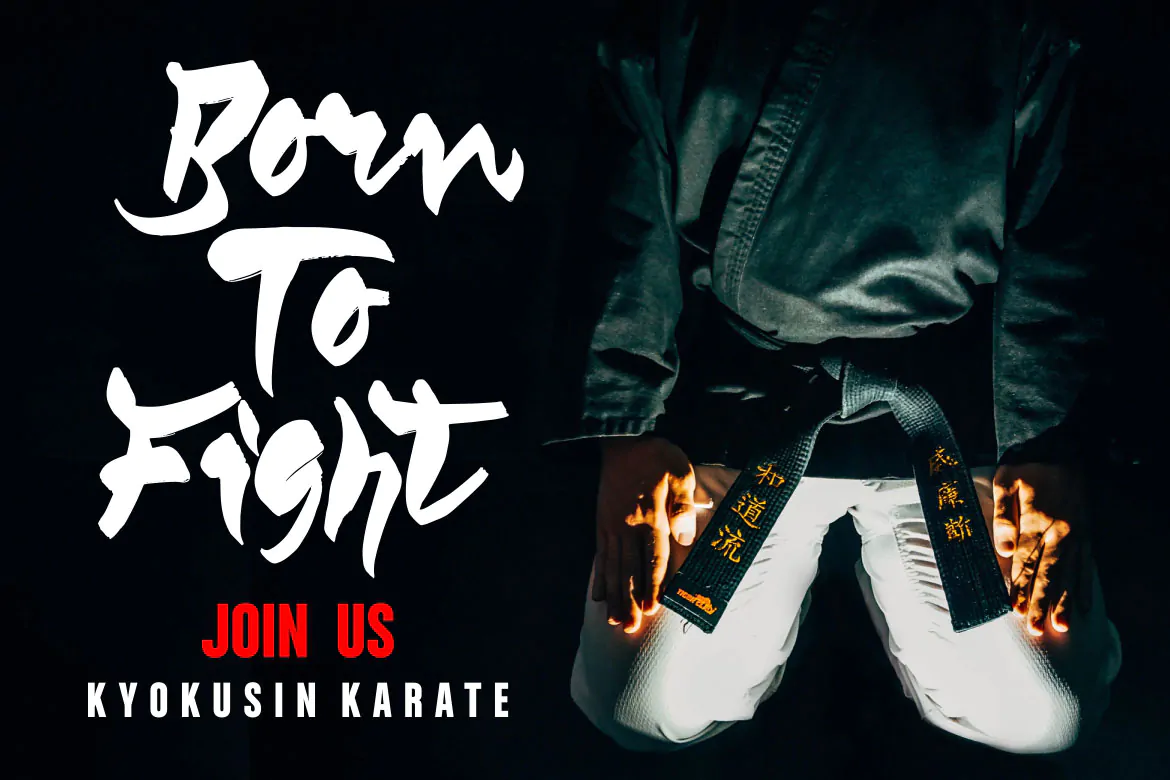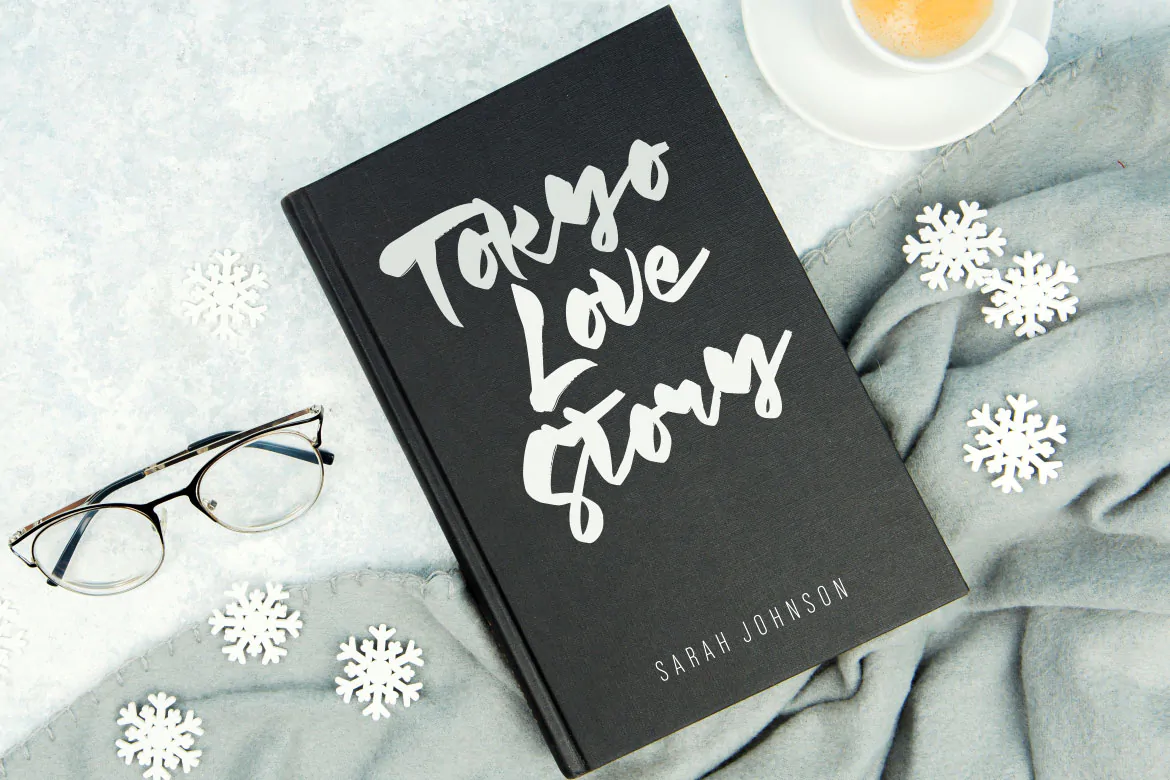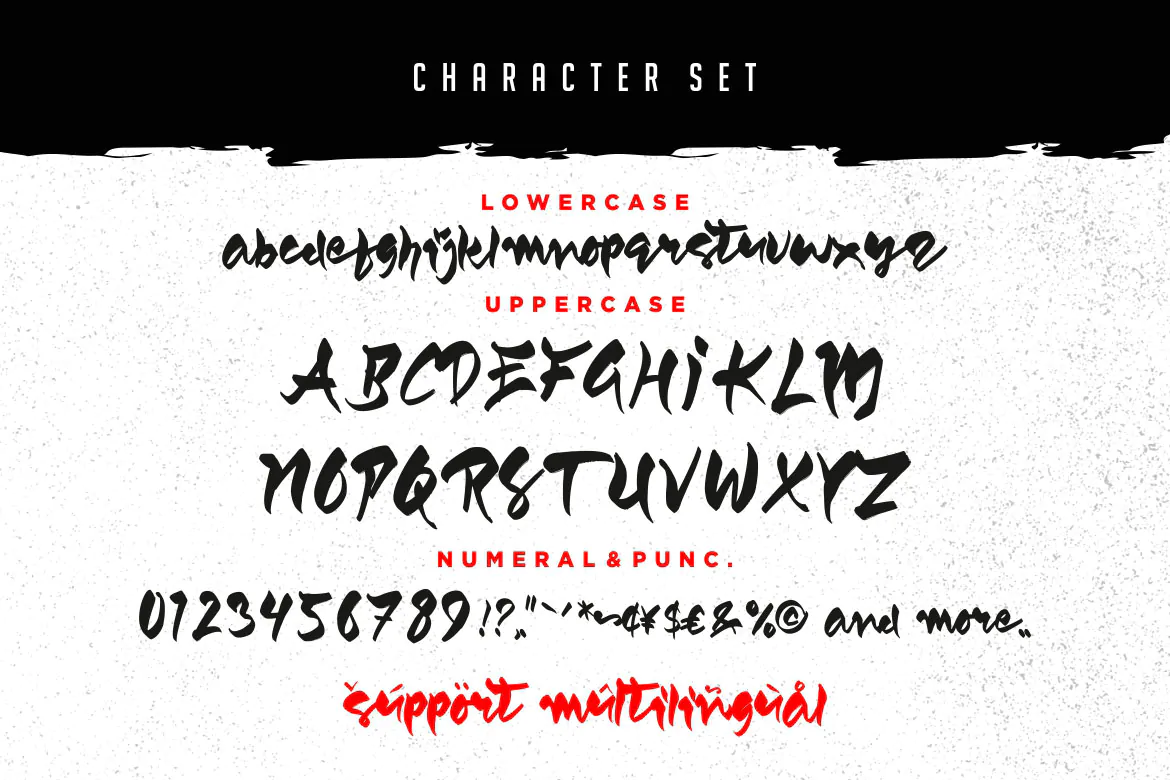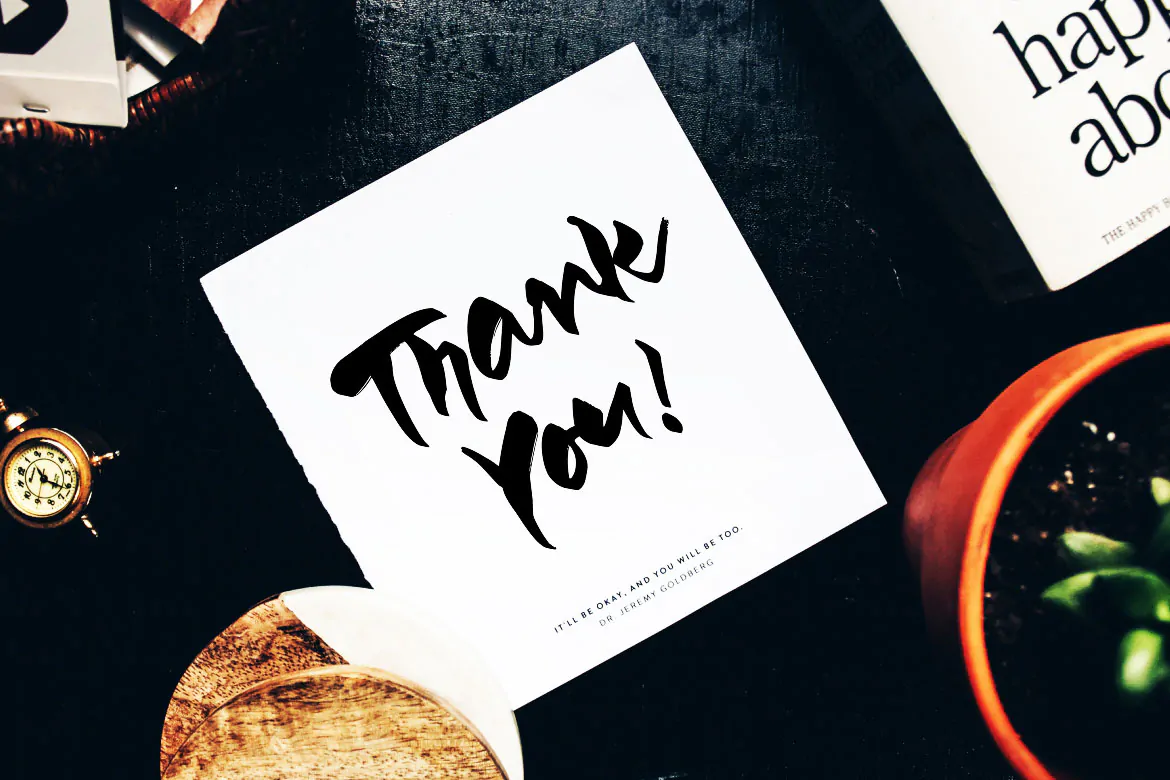
فونت سبک نینجا Santoriu
فونت سبک نینجا انگلیسی
فونت سبک نینجا Santoriu یک قلم انگلیسی فوق العاده زیبا است که مناسب جهت استفاده در طرح و پروژههای گرافیکی مختلف میباشد. این فونت زیبا با وزن معمولی طراحی شده است که میتوانید از آن در طراحی انواع پوستر، چاپ روی تیشرت، بسته بندی محصولات، ظروف یکبار مصرف کاغذی، لوازم التحریر و … استفاده کنید.